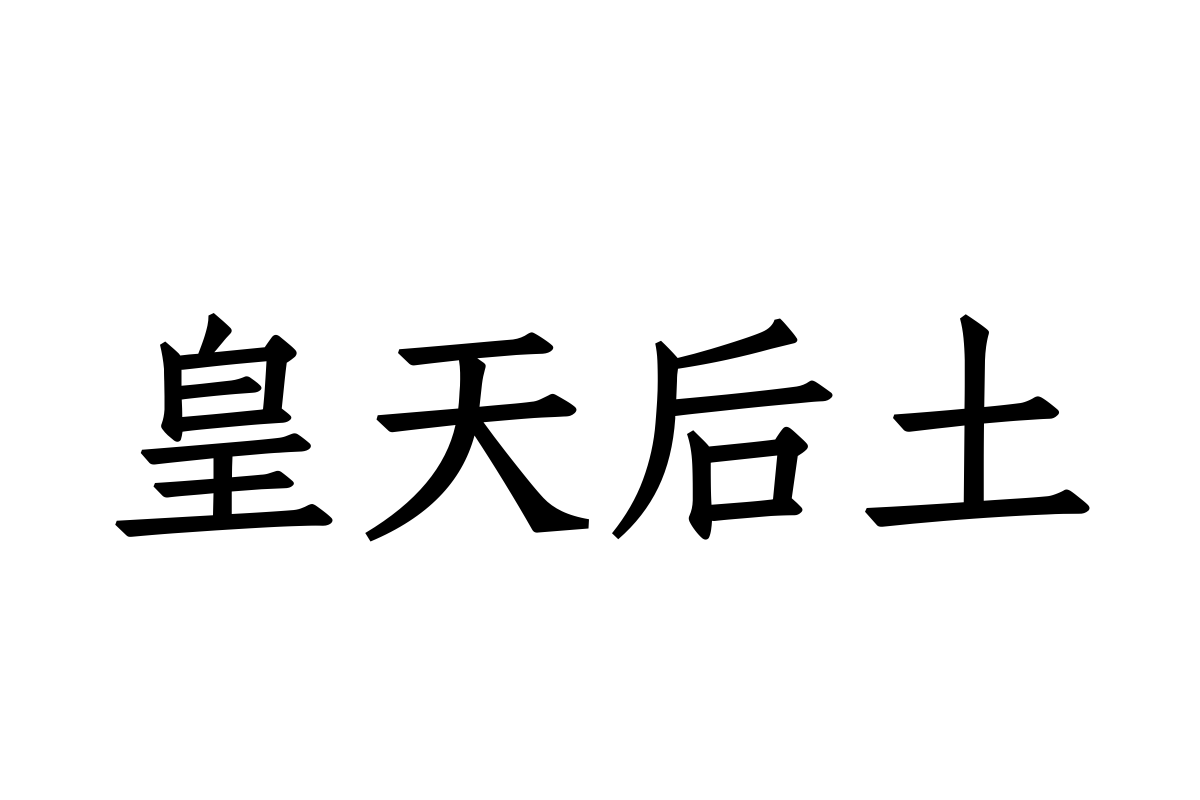
汉仪书仿65s是一款专为书法设计制作的中文字体。它继承了传统书法的韵味,同时又融入了现代审美的元素,使得这款字体既有古典之美,又不失时尚气息。
这款字体笔画流畅,结构严谨,每个字都经过精心设计,力求达到最佳的书写效果。无论是楷书、行书还是草书,都能够轻松驾驭。同时,它的字形大小适中,适合各种场合的书写需求。
汉仪书仿65s的字体风格独特,既适合正式的商务场合,也适合日常的书写娱乐。无论是作为个人使用,还是用于商业设计,这款字体都能展现出其独特的魅力。
总的来说,汉仪书仿65s是一款非常适合书法爱好者和设计师使用的中文字体。它不仅能够提升你的书写水平,还能让你的设计作品更加出彩。